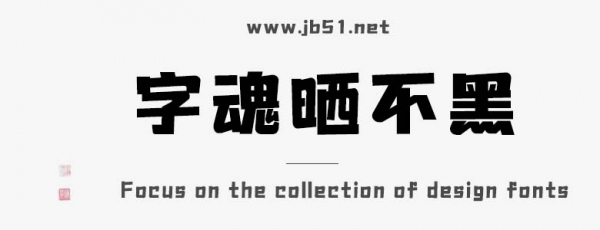
字魂曬不黑字體是由字魂字庫推出的黑體字體,該字體包含7144個中文、字母、 符號和數(shù)字,具有簡約的風(fēng)格,具有中國風(fēng)的風(fēng)格,適合應(yīng)用于藝術(shù)設(shè)計、平面宣傳設(shè)計、網(wǎng)頁設(shè)計,書法字帖等領(lǐng)域。
字魂曬不黑字體是一款商用的黑體字體,該字體包含7144個中文、字母、 符號和數(shù)字,具有簡約的風(fēng)格,可以滿足您設(shè)計上的各種需求,該字體主要用于化妝美容等場景, 您不但可以在字魂網(wǎng)下載字魂曬不黑字體,同時還有眾多毛筆書法字體、創(chuàng)意字體等可供選擇!